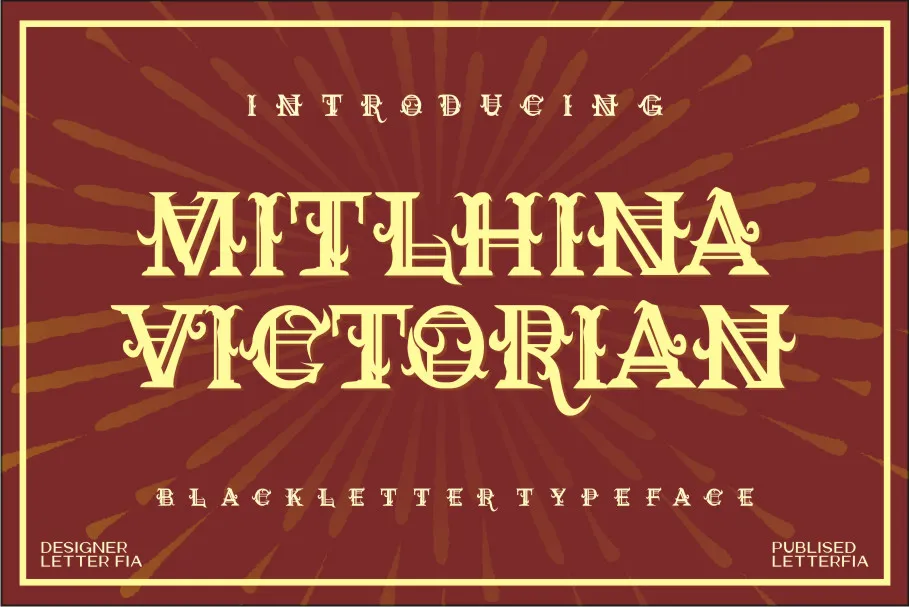
Mitlhina Victorian Font – Download Grátis
A fonte Mitlhina Victorian é uma escolha perfeita para quem procura um estilo robusto e detalhado, ideal para projetos que exigem uma expressão assertiva e distintiva. Sua natureza gothic torna-a especialmente atraente para aplicações de design gráfico, como letras do título ou logotipos, garantindo um toque único e inconfundível em qualquer projeto. Oferecida pela Letterfiastudio, esta fonte blackletter traz a sofisticação dos tempos vitorianos junto com a modernidade que o designer contemporâneo valoriza. Com uma aparência poderosa e detalhada, ela é perfeita para quem busca um toque distintivo em qualquer projeto de design. Escolha Mitlhina Victorian para dar ao seu projeto aquele toque único que faz toda a diferença.
Designer: letterfiastudio